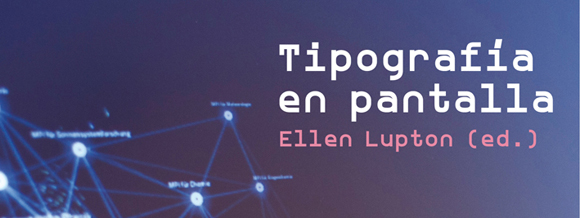
Seguro que preguntamos a cualquier diseñador gráfico por un título de un buen manual de tipografía y nos dice unos cuantos. Creo que el mercado de manuales de tipografía está bien surtido. Ya sábeis, breve reseña histórica, alguna receta clásica sobre composición, el tipo como imagen… pero cuando preguntamos por algún título sobre tipografía para pantalla la cosa cambia. Aún siendo un campo en pleno desarrollo los trabajos teóricos sobre tipografía en este nuevo soporte, con unas características totalmente diferentes a la tipografía sobre papel, no son fáciles de encontrar.
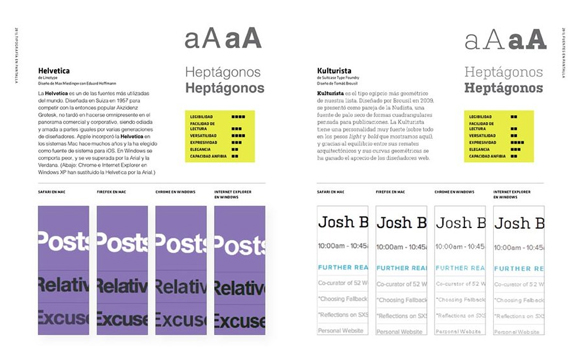
La prolífica autora, docente e investigadora Ellen Lupton, creadora del muy recomendable Pensar con tipos, ha editado, apoyada en el trabajo de un grupo de estudiantes del MICA de Baltimore, un libro sobre el tema que intenta dar respuesta a muchas de las preguntas que nos podemos plantear en torno a la utilización de la tipografía en pantalla, en un entorno cuya principal característica es la emisión de luz y la presentación dinámica de los contenidos. Este libro ha sido traducido y editado en España por la editorial Gustavo Gili y lleva por título «Tipografía en pantalla».
Los contenidos del mismo se articulan en torno a unos conceptos básicos: selección de tipografías, presentación de la tipografía en pantalla y la composición de textos y otra parte en la que claramente se apuesta por la interfaz gráfica, la animación y el código. Un aspecto importante de los contenidos de esta parte es que vienen apoyados por estudios de casos prácticos que arrojan luz sobre los diferentes temas tratados. Asimismo el aspecto de la tipografía como signo gráfico está tambien contemplado en un capítulo sobre creación de iconos y logotipos.
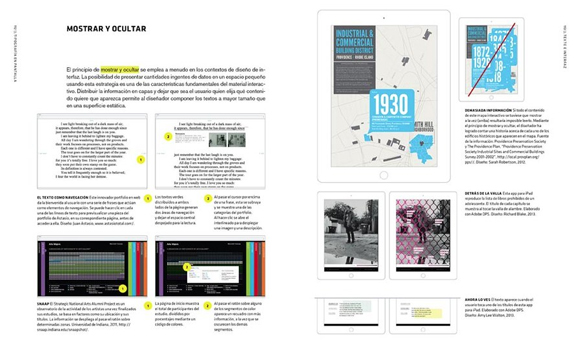
En definitiva, creo que Tipografía en pantalla es un buen título introductorio para un tema bastante complejo como es el de la tipografía en pantalla. El lector puede hacerse una buena idea sobre las distintas características y condicionantes que se presentan al trabajar con la tipografía en este soporte así como obtener una buena visión panorámica del estado actual de su desarrollo en cuanto a su implementación y posibilidades.
Tipografía en pantalla
Una guía para diseñadores, editores, tipógrafos, blogueros y estudiantes
Ellen Lupton (ed.)